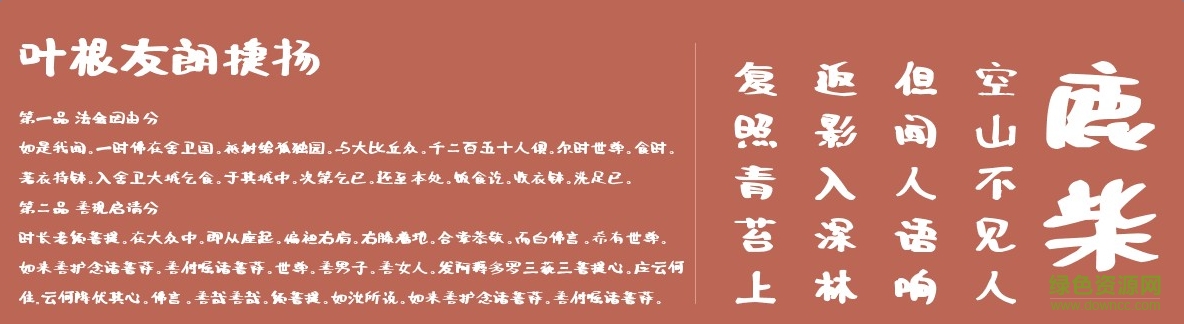
葉根友朗捷揚(yáng)字體是一款由知名書法家葉根友創(chuàng)造的字體,比劃圓潤(rùn),適用于廣告、藝術(shù)設(shè)計(jì),海報(bào)設(shè)計(jì)等方面,有需要的朋友們不要錯(cuò)過(guò)了。歡迎大家來(lái)綠色資源網(wǎng)踴躍下載哦!
葉根友朗捷揚(yáng)字體是一款特殊的字體,不是傳統(tǒng)的毛筆書寫,是用IPAD和手指寫成的,感謝高科技帶給我們的書法體驗(yàn),這樣的創(chuàng)作很美妙,相信以后還會(huì)出來(lái)更多這樣科技與書法結(jié)合的字體作品,這套葉根友破若墨極的字體的筆畫與傳統(tǒng)的毛筆創(chuàng)作的筆鋒是完全不一樣的,包含圓角,點(diǎn)、橫等都有令人意想不到的效果。
葉根友朗捷揚(yáng)字體,用途廣泛,是葉根友先生的手寫字體,適合場(chǎng)合很多,各位字體收藏者可以來(lái)看看。